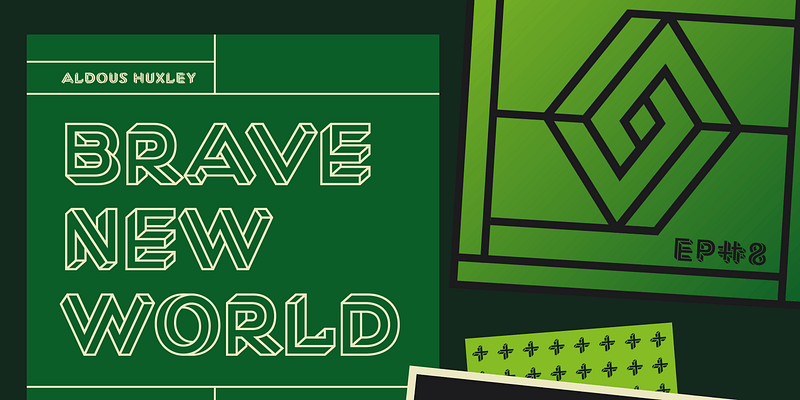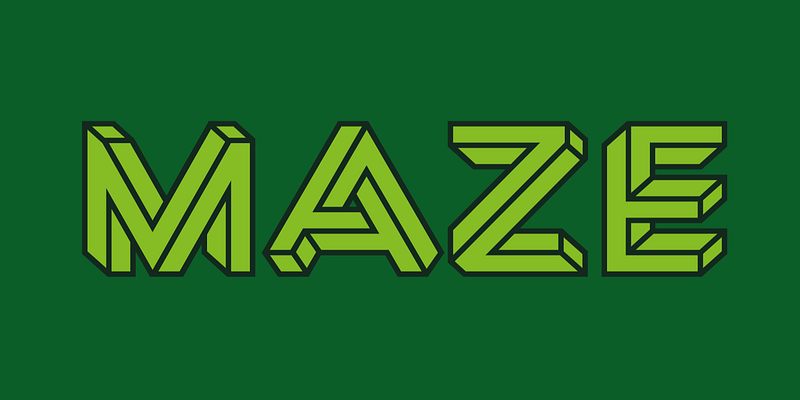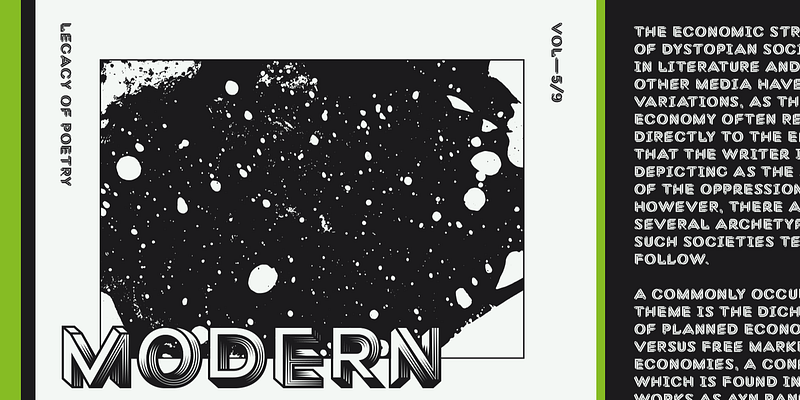
Macula는 도저히 있을 법하지 않은 서체입니다. Jacques Le Bailly는 Oscar Reutersvärd가 고안한 착시 도형인 펜로즈 삼각형과 상징적인 MC Escher의 예술 작품에서 방향 감각을 잃게 만드는 관점을 차용하여 현실 세계에 물리적으로 존재할 수 없는 놀라운 3차원 서체를 만들었습니다. 상황별 대체는 보다 한 문자에서 다음 문자로 시점을 뒤집어 보다 분명한 효과를 연출합니다. 이 서체는 다색 디스플레이 설정으로 레이어링할 수 있는 구성 요소 스타일을 제공합니다. Bold Monday, 2012.